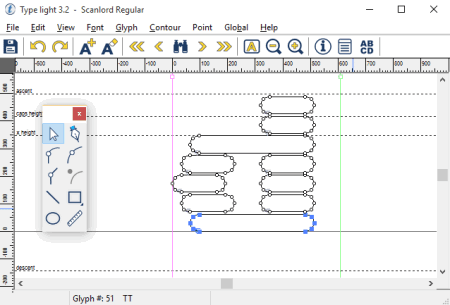
– Glowtxt
Glowtxt adalah generator font online sederhana untuk membuat teks indah sebagai file PNG atau GIF. Cukup pilih ukuran dan gaya yang Anda inginkan dari menu tarik-turun, centang apakah Anda ingin menambahkan animasi atau efek cahaya, dan mengubah warna latar belakang cahaya. Setelah Anda puas, Anda dapat mengklik tombol unduh. Jika Anda tidak menambahkan efek cahaya atau animasi, maka itu akan diunduh sebagai file PNG. Jika ya, itu akan diunduh sebagai GIF.
– Font Meme
Font Meme adalah generator font online gratis yang dapat Anda gunakan untuk membuat jenis huruf menarik yang terinspirasi oleh merek dan logo favorit Anda. Anda dapat mengklik Harvard Business Review, misalnya, dan mengetahui bahwa itu menggunakan font National 2 Bold. Karena ini adalah font premium, Anda akan diundang untuk mengklik tautan untuk membeli font, lalu kembali ke Font Meme untuk mengunggahnya.Anda juga dapat menelusuri koleksi font gratis, pilih salah satu, lalu pilih warna dan efek dan tekan “Generate.” Anda kemudian dapat menyematkan font ini menggunakan cuplikan HTML yang dibuat secara otomatis atau tautan gambar langsung.
– Stylish Text Generator
Stylish adalah solusi paling sederhana untuk mengubah karakter dalam kata atau frasa dan mengelilingi kata atau frasa. Di bawah “Efek Teks”, Anda dapat menambahkan karakter khusus, simbol, dan karakter bahasa lainnya dalam teks Anda. Di bawah “Dekorasi Teks”, saya dapat menambahkan karakter di sekitar teks. Jika sudah siap, saya dapat mengeklik “Buat” dan cukup salin dan tempel hasilnya ke situs web, platform media sosial, atau aplikasi perpesanan saya.
– Cool Text
Cool Text adalah alat online gratis yang memungkinkan Anda membuat desain logo atau mengunduh font gratis dengan cepat. Yang harus Anda lakukan adalah memilih gaya teks yang Anda inginkan, memasukkan teks Anda, memilih warna Anda, menambahkan efek bayangan dan gambar jika diinginkan, dan membuat logo Anda. Anda kemudian dapat mengunduhnya sebagai file PNG atau mengisi formulir untuk mendapatkan kode HTML.
– Online Text Generator
Jika Anda penggemar berat font grafis, maka Online Text Generator adalah solusi untuk Anda. Ini akan membantu Anda membuat font khusus berdasarkan berbagai tema yang saat ini mereka dukung. Tema-tema ini termasuk 3D, gelembung, gothic, grafiti, kaligrafi, dan teks kartun. Dalam setiap tema, ada gaya berbeda yang dapat Anda pilih, menjadikannya alat yang sangat serbaguna. Anda juga dapat memilih ukuran gambar dan font dan warna font dan latar belakang. Saat Anda siap, klik “Buat” lalu sematkan gambar dengan kode HTML.
– Instagram Fonts
Instagram Fonts adalah pembuat font online yang dirancang khusus untuk Instagram, tetapi juga akan berfungsi di situs web apa pun. Dengan alat ini, Anda mengetik teks ke dalam bidang input dan opsi jenis huruf yang berbeda dihasilkan secara otomatis. Setelah Anda melihat gaya yang Anda suka, Anda cukup menyalin dan menempelkannya ke bio profil atau situs Anda. Bagian terbaiknya adalah ini adalah font Unicode yang akan selalu muncul terlepas dari perangkat atau browser yang digunakan pengguna Anda.
– Font Generator
Dengan Font Generator, Anda mulai dengan memilih dari sejumlah kategori font, seperti tulisan tangan, gothic, dan elegan. Dalam setiap kategori, ada beberapa gaya untuk dipilih. Anda dapat mengklik salah satu dan kemudian menyesuaikan ukuran font, warna, dan warna latar belakang. Anda kemudian memiliki opsi untuk mengunduhnya sebagai file PNG, JPG, atau GIF. Satu-satunya downside adalah bahwa akan ada branding untuk Font Generator yang disertakan dalam logo.
– Flaming Text
Flaming Text adalah layanan gratis yang memungkinkan Anda membuat logo luar biasa berdasarkan banyak pilihan template. Misalnya, dari pilihan di bawah ini, Anda dapat mengeklik gaya kiri atas yang disebut “Komik”. Kemudian, Anda dapat memilih dari variasi yang telah dirancang sebelumnya dengan warna, efek gradien, dan warna latar belakang yang berbeda. Atau, Anda dapat menyesuaikannya sendiri, lalu mengunduh produk akhir sebagai file PNG atau membuat akun untuk mendapatkan kode HTML.
– TextFX
TextFX.co adalah pembuat font gratis yang memungkinkan Anda membuat logo atau spanduk dengan teks khusus. Untuk memulai, pilih font yang ingin Anda gunakan dari menu tarik-turun dan ketik kata atau frasa. Anda dapat mengubah warna jika Anda mau. Setelah itu, pilih gaya dari semua gaya yang mereka cantumkan di halaman. Terakhir, pilih pola latar belakang. Anda kemudian dapat mengunduh gambar sebagai JPEG atau PNG, lalu memasukkannya ke situs Anda.